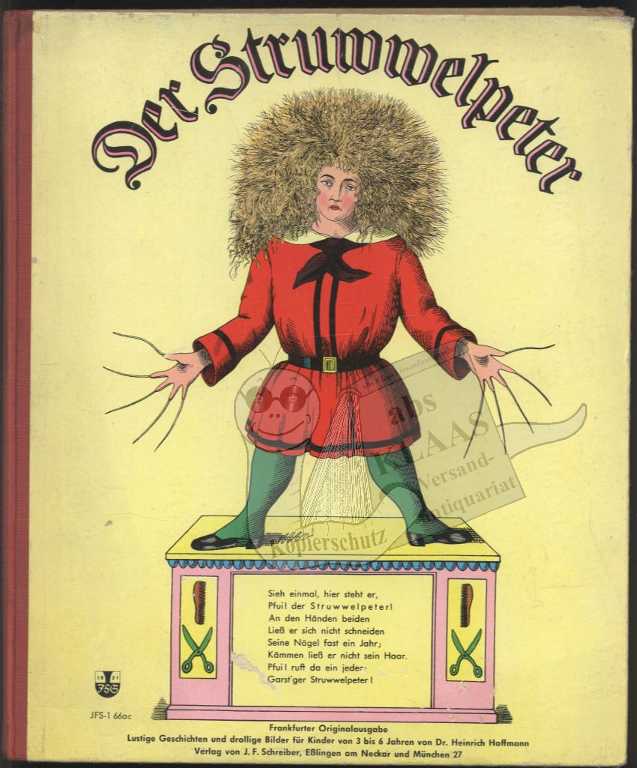
Schrift/Gestalter gesucht (Struwwelpeter)
ich suche Informationen zu Schrift/Gestalter des Covers von Struwwelpeter:
Auch nach längerer Suche habe ich keine Infos gefunden - vermutlich gibt es die Fraktur Schrift bis heute gar nicht digitalisiert? Kennt jemand Buchcover mit ähnlicher Schrift?
Oh danke sehr! Im Grund meine ich auch die "Hellen Striche", aber vor allem die dekorative Form, gerade bei der Versalien, "dezent" aber dennoch extrem bestimmend.